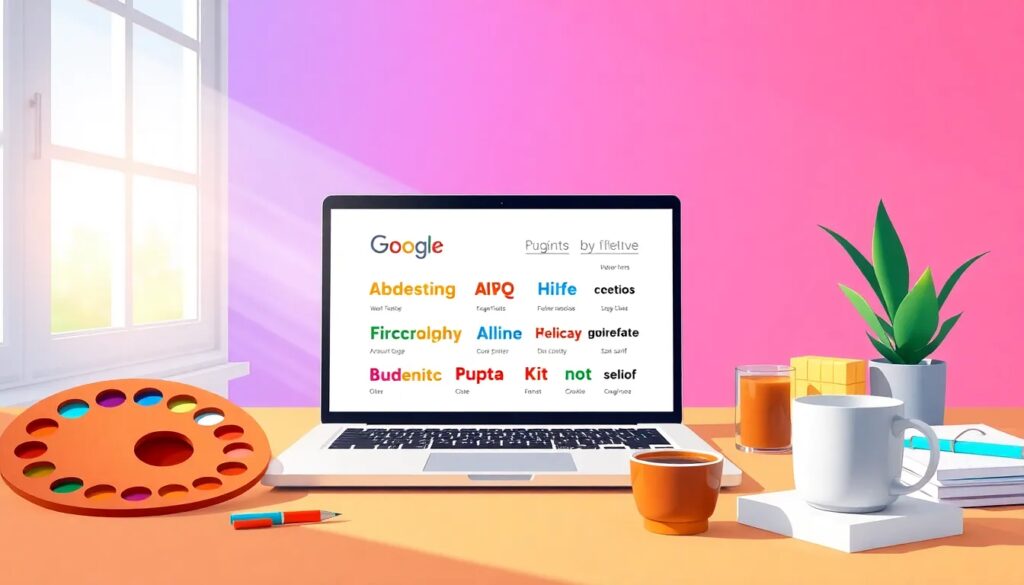
Web font Google: qué son y cómo usarlas
En el mundo del diseño web, la tipografía juega un papel crucial en la experiencia del usuario. Google Fonts es una herramienta que permite a los diseñadores acceder a una amplia variedad de fuentes de manera gratuita. Este artículo explora cómo implementar estas fuentes y mejorar tu sitio web.
La integración de Google Fonts no solo embellece tu diseño, sino que también puede influir en el rendimiento y SEO de tu página. A continuación, vamos a analizar en detalle qué son estas fuentes y cómo optimizarlas.
Uso de Google Fonts en el diseño web
Las Google Fonts ofrecen más de 1400 familias tipográficas que puedes utilizar en tu web. Esto te permite personalizar la apariencia de tu sitio y crear una identidad visual única. Además, la implementación es sencilla, ya que solo necesitas incluir unas líneas de código en tu CSS.
Un beneficio destacado de usar web fonts google es que son compatibles con la mayoría de los navegadores modernos. Esto asegura que tus visitantes vean el diseño tal como lo imaginas, independientemente del dispositivo que utilicen.
Es importante mencionar que el uso de estas fuentes puede influir en el rendimiento de tu página. Por ello, optimizar su carga es fundamental. A continuación, te explicaremos cómo hacerlo de manera efectiva.
¿Qué son las Google Fonts?
Google Fonts es una biblioteca de fuentes tipográficas que se puede utilizar de forma gratuita en proyectos web. Estas fuentes están diseñadas para ser implementadas fácilmente y optimizadas para la web, permitiendo a los diseñadores crear páginas visualmente atractivas.
La ventaja de usar Google Fonts radica en su amplia variedad y en la facilidad de integración. Además, al ser alojadas en un CDN (Content Delivery Network), se minimiza el tiempo de carga. Esto es fundamental para mantener una buena experiencia de usuario.
Las Google Fonts también se pueden adaptar a diferentes estilos y necesidades, desde tipografías serif hasta sans-serif. Esto permite a los diseñadores elegir la que mejor se adapte a la identidad de su marca o proyecto.
Ventajas de usar Google Fonts en tu web
- Facilidad de uso: La integración es rápida y sencilla, lo que ahorra tiempo en el desarrollo.
- Optimización del rendimiento: Al ser servidas desde un CDN, las fuentes se cargan rápidamente.
- Compatibilidad: Son compatibles con todos los navegadores y dispositivos.
Además de estas ventajas, el uso de web fonts google puede mejorar la legibilidad de tu contenido. Una buena tipografía ayuda a que los usuarios permanezcan más tiempo en tu página, lo que puede disminuir las tasas de rebote.
Este proceso es esencial para asegurar que tu sitio aproveche al máximo las ventajas de las tipografías de Google. Además, puedes combinar varias fuentes para crear un diseño más dinámico y atractivo.
Mejores prácticas para usar Google Fonts sin afectar al rendimiento
Para maximizar el rendimiento de tu web al usar Google Fonts, es recomendable seguir ciertas prácticas:
- Utiliza la propiedad CSS display=swap para evitar que se muestre un texto sin fuente mientras se carga.
- Limita el número de fuentes que utilizas. Menos es más.
- Selecciona solo las variantes de las fuentes que realmente vas a usar (por ejemplo, solo regular y negrita).
- Aloja las fuentes localmente si es posible, especialmente si la carga de tu web es una prioridad.
Implementar estas prácticas no solo mejorará la velocidad de carga de tu web, sino que también proporcionará una mejor experiencia de usuario.
Las fuentes más populares de Google Fonts
A continuación, te presentamos algunas de las fuentes más populares que puedes encontrar en Google Fonts:
- Roboto: Muy utilizada por su legibilidad y versatilidad.
- Lato: Ideal para sitios modernos y minimalistas.
- Open Sans: Ampliamente utilizada en proyectos digitales por su claridad.
- Montserrat: Perfecta para títulos y secciones destacadas.
Elegir la fuente adecuada puede impactar significativamente en la percepción de tu marca y en la experiencia del usuario. Asegúrate de seleccionar fuentes que se alineen con el mensaje que deseas comunicar.
En resumen, las Google Fonts son una herramienta valiosa para cualquier diseñador web. No solo aportan variedad y estilo, sino que también son una opción eficaz para optimizar el rendimiento y la experiencia del usuario. Utilizar estas fuentes correctamente puede hacer una gran diferencia en la percepción de tu marca y en el éxito de tu sitio web.